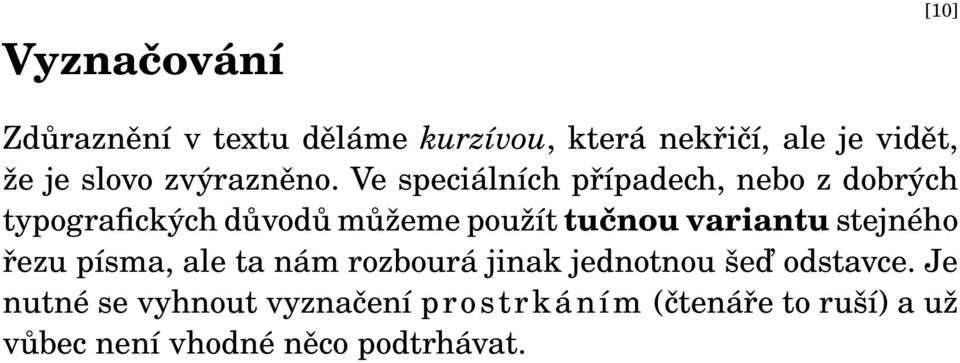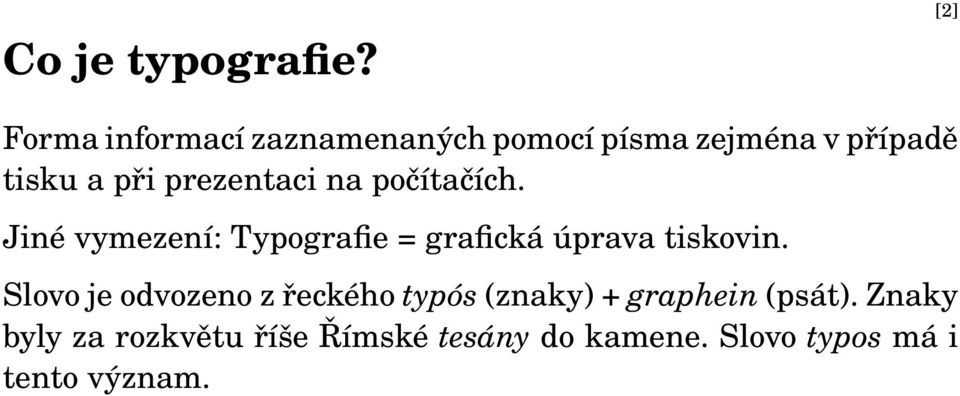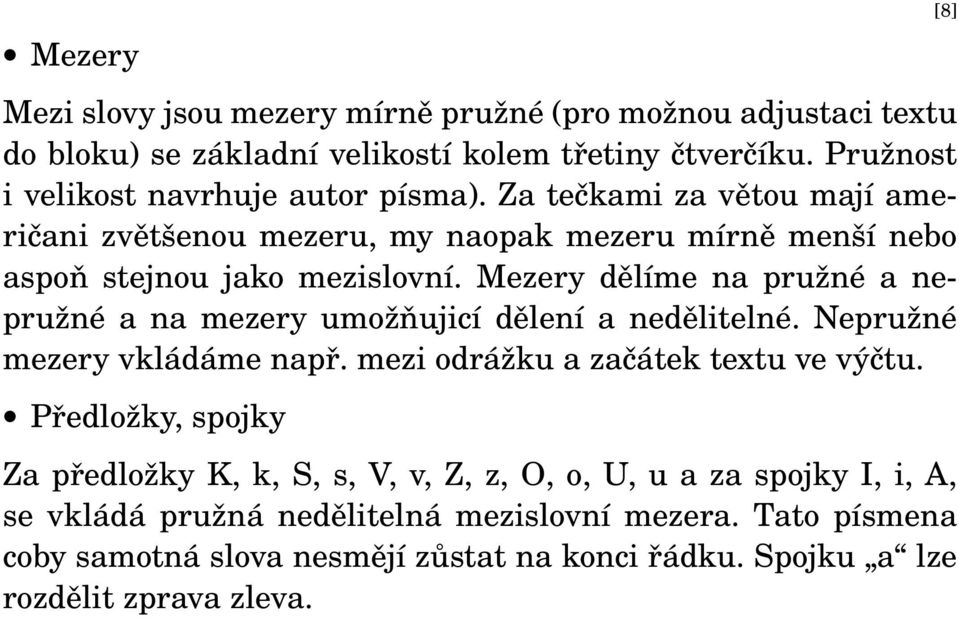
[1] Typografie.
1 [1] Typografie
2 Co je typografie? [2] Forma informací zaznamenaných pomocí písma zejména v případě tisku a při prezentaci na počítačích. Jiné vymezení: Typografie = grafická úprava tiskovin. Slovo je odvozeno z řeckého typós (znaky) + graphein (psát). Znaky byly za rozkvětu říše Římské tesány do kamene. Slovo typos má i tento význam.
3 Dobrá typografie? [3] Není vidět. Je nerušivým nástrojem ke sdělení obsahu informace. Ctí nejdůležitější pravidlo: čitelnost. Čtenář nesmí být unavován ani rušen. Podřizuje se staletým tradicím. Jen u některých akcidenčních tiskovin může v rozumné míře typografie vyčnívat. Pak se blíží užitnému umění.
4 Rámcová pravidla pro knihu [4] Levá, pravá stráka, dvoustrana. Stránkový rejstřík. Titulky kapitol, sekcí,... Členění textu na odstavce (vdovy, sirotci). Patitul, protitul, titul, vydavatelský záznam, předmluva/úvod, obsah, tiráž. Stránkové číslice, záhlaví. Seznam literatury, seznam zkratek, rejstřík.
5 Mikrotypografická pravidla [5] Dříve byla tato pravidla zahrnuta do ON , ta přestala platit v roce Spojovník (-) Propan-butan, dělení slov, zvádne-li to sám, ISBN , slovník česko-anglický. Pomlčka na čtverčík ( ) a na půlčtverčík ( ) Chceme-li oddělit části věty od jiné části věty. Kratší pomlčka ve významu až, nebo dálnice Praha Brno. V těchto případech bez mezer kolem. Další vodorovné čárky : mínus a podtržítko. Třeba ve vzorci a 2 b 2 je první minus unární (bez mezery) a druhé minus binární (s malými mezerami z obou stran). Podtržítko se nepoužívá.
6 Tečky čárky, středníky. Nemají před sebou mezeru, za sebou mezeru mají. Otazník, vykřičník, dvojtečka mají před sebou vlasovou mezeru (nedělitelnou) nebo (není-li k dispozici) nemají před sebou mezeru žádnou. Závorky nemají zevnitř mezeru, z vnějšku ano. Sazba data nebo 23. května (Všimněte si mezer za tečkami, lidé je tam často nedávají!) Interpunkce pro konec věty je v závorce, pokud je v závorce celá věta (viz předchozí závorka), jinak je čárka a tečka až za závorkou (jako zde). I ve zkratce s. r. o. jsou mezery za tečkami, ale zúžené. Výpustka neboli elipsa (... ) má často ve fontu svůj obraz, když ne, pak musí být vhodně vzdušná... Samotné tři tečky vedle sebe jsou často nevhodně natlačeny na sebe..., takže to by se vyskytovat nemělo. Výpustka na konci věty nemá za sebou čtvrtou tečku. [6]
7 Uvozovky V českém jazyce se používají takovéto uvozovky, velmi výjimečně též»takové«uvozovky. Ačkoli jsme si je vypůjčili od francouzů, používáme je opačně než oni. Uvozovky uvnitř uvozovek mohu být,jednoduché. Je diletantismus používat symbol palce místo uvozovek! V angličtině se používají takovéto uvozovky. Stupeň ( ), procento (%), jednotky Stupeň se sází s malou nedělitelnou mezerou za číslovkou: 10. Symbol se přilepí na písmeno C, jedná-li se o stupně celsia: 10 C. Procento ve výzmanu čtyřprocentní se váže na číslovku (4%), ale ve významu čtyři procenta musí mít mezi číslovkou a procentem nedělitelnou mezeru (4 %). Jednotky měr a vah mají mezi číslovkou a jednotkou nedělitelnou třetinovou mezeru (15 km). [7]
8 Mezery Mezi slovy jsou mezery mírně pružné (pro možnou adjustaci textu do bloku) se základní velikostí kolem třetiny čtverčíku. Pružnost i velikost navrhuje autor písma). Za tečkami za větou mají američani zvětšenou mezeru, my naopak mezeru mírně menší nebo aspoň stejnou jako mezislovní. Mezery dělíme na pružné a nepružné a na mezery umožňujicí dělení a nedělitelné. Nepružné mezery vkládáme např. mezi odrážku a začátek textu ve výčtu. Předložky, spojky Za předložky K, k, S, s, V, v, Z, z, O, o, U, u a za spojky I, i, A, se vkládá pružná nedělitelná mezislovní mezera. Tato písmena coby samotná slova nesmějí zůstat na konci řádku. Spojku a lze rozdělit zprava zleva. [8]
9 Dělení slov Dělíme podle slabik. Ovšem nedělíme tak, aby na konci řádku zůstalo jediné písmeno (o-/hmatat) a pokud to je možné, nenecháváme ani na dalším řádku dvě a méně písmen (odva-/ha). Také nedělíme tak, aby vznikla slova vulgární nebo vyvolávající nevhodnou asociaci (sle-/pička, kni-/hovna, tele-/vize, tlu-/močím). Dělení v mezerách Dělit implicitně lze v každé mezeře. Výjimku tvoří mezery za předložkami (viz výše) a dále na mnoha dalších místech: za tečkou v datu, v mezeře mezi číslovkami a jednotkami, mezi trojcifernými úseky delšího čísla, před pomlčkou, za tečkami ve víceznakových zkratkách (s. r. o.), před výpustkou (... ). Korektor vždy přejede zrakem pravou hranu textu a během chviličky rozpozná chybná dělení. [9]
10 Vyznačování [10] Zdůraznění v textu děláme kurzívou, která nekřičí, ale je vidět, že je slovo zvýrazněno. Ve speciálních případech, nebo z dobrých typografických důvodů můžeme použít tučnou variantu stejného řezu písma, ale ta nám rozbourá jinak jednotnou šeď odstavce. Je nutné se vyhnout vyznačení prostrkáním (čtenáře to ruší) a už vůbec není vhodné něco podtrhávat.
11 Korektury [11] podle důležitosti dokumentu profesionální korektoři a korektorské značky autor může dělat korektury svého textu až několik dní po napsání často pomůže vytisknout si dokument a odpočinout si od počítačového monitoru u důležitějších dokumentů nechá autor zkorikovat text někým jiným (nemusí se nutně jednat o profesionálního korektora).
12 [12]
13 Zalomení odstavce [13] Pravý praporek nebo adjustace do bloku Volba odstavcové zarážky a řešení východové řádky Vertikální mezery mezi odstavci Při adjustaci do bloku pružíme v mezislovních mezerách, spíše stlačujeme než roztahujeme. Je krajně nevhodné pružit v mezerách mezi písmeny uvnitř slova, vypadá to jako slovo zdůrazněné prostrkáním a navíc to ruší čtenáře. Lepší systémy dovolí mírnou deformaci písmen (rozšíření, zúžení), které musí mít meze nastaveny tak, aby to oko čtenáře nepostřehlo. Někdy je možné nastavit zlom do režimu visící interpunkce (jako v předchozím odstavci). Vyvolá se tím lepší pocit kompaktního bloku, protože spojovníky uvnitř bloku narušují pravou hranu sazby.
14 Matematická sazba [14] Proměnné (a obecně označení matematických objektů) sázíme výhradně kurzívou, nic dalšího není skloněno: číslice (pořadové), závorky a další symboly, ustálené znaky pro funkce, limity, fyzikální jednotky atd., vše je vzpřímeno. Dojde-li matematikům abeceda (což je velmi časté), mají dále řecká písmena (mínusky kurzívou, verzálky vzpřímené), zdvojené tahy, skripty, frakturu. Vektory: podtržení nebo šipka nebo bold sans serif skloněný. Osa matematické sazby, tečka na ose, tři tečky dle kontextu. Mezery kolem binárních operací a relací, rozlišovat < a. Indexy, exponenty (100, 70, 50). Vzorec v odstavci a na samostatném řádku.